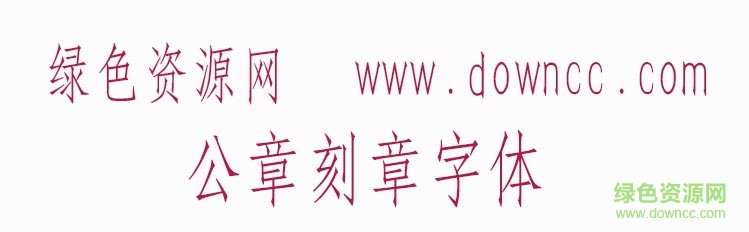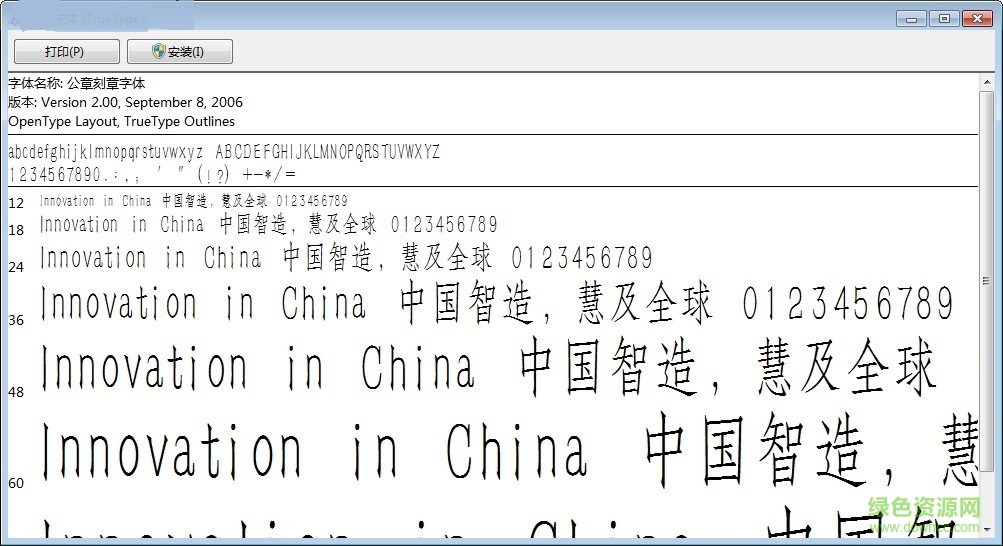
公章刻章專用字體
公章刻章字體是一款專為刻章打造的一款標(biāo)準(zhǔn)字體,可能很多人都不知道其實(shí)刻章都會(huì)有一套基本的規(guī)章字體,不然很多時(shí)候刻出的印章都是不合格的,現(xiàn)在這款字體完完全全國家標(biāo)準(zhǔn),歡迎有需要的用戶下載。
公章刻章字體
公章刻章字體簡介:
公章刻章字體是使用非常流行廣泛的字體軟件,字體筆直流暢形體端正,常用于美工設(shè)計(jì)和印刷打印等多種領(lǐng)域,下載安裝即可使用。